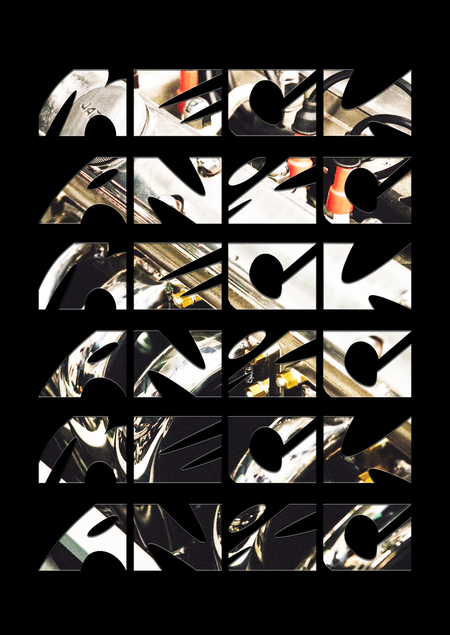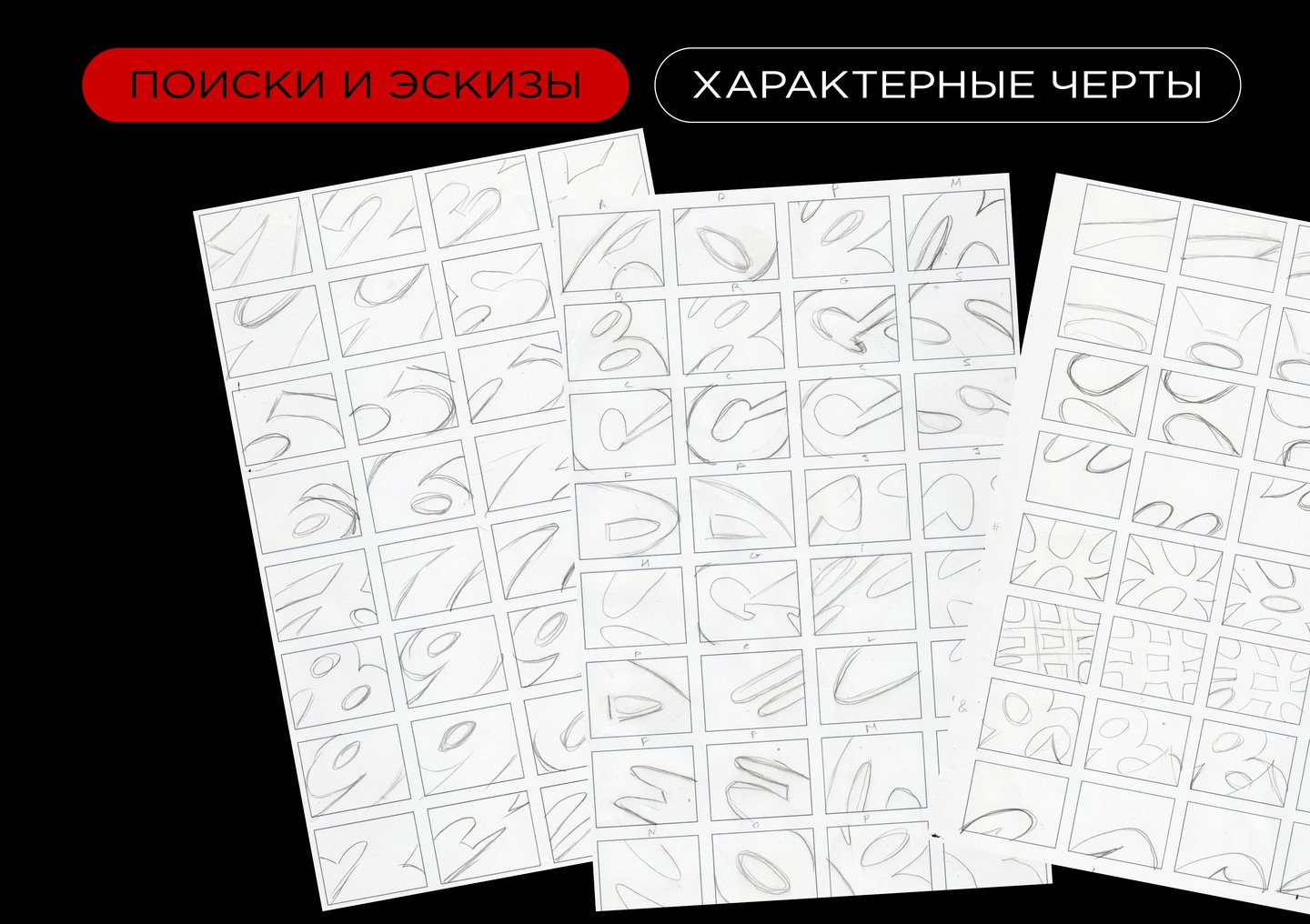
mechanic font
В проекте шрифта Mechanic Font каждая буква рассматривается как условный «блок цилиндров» с вырезанными каналами и полостями, напоминающими систему поршней, трубок и креплений. Цель шрифта — передать движение и силу двигателя, создать настроение машинной эстетики.